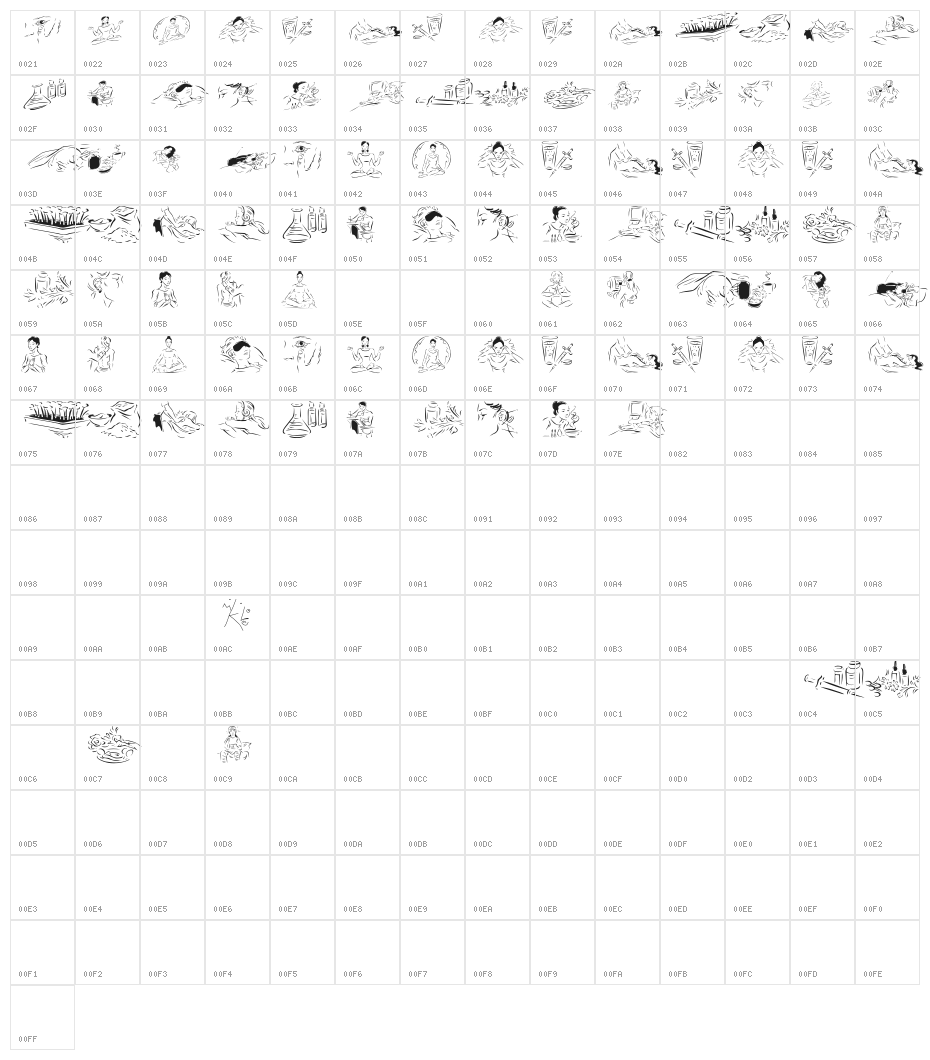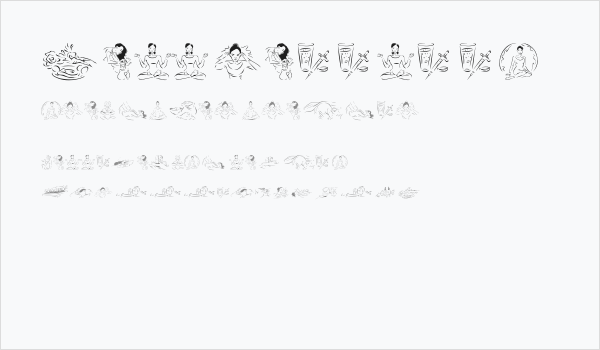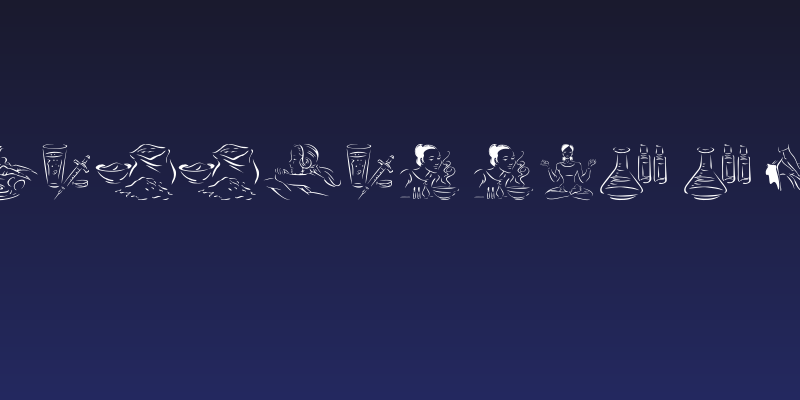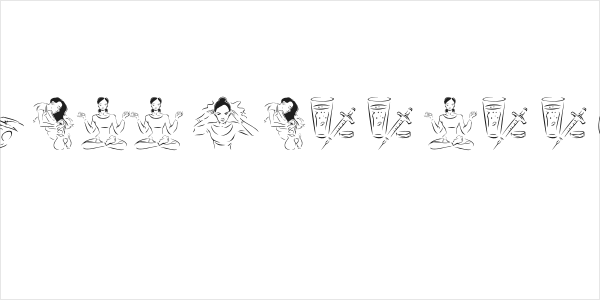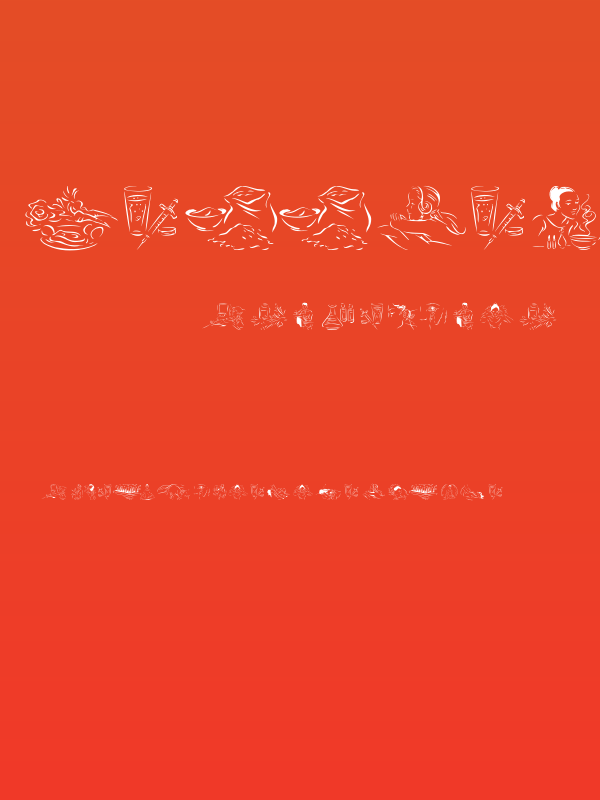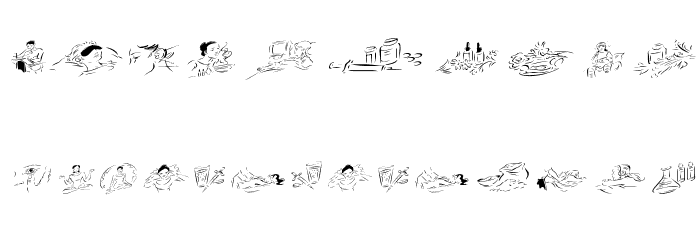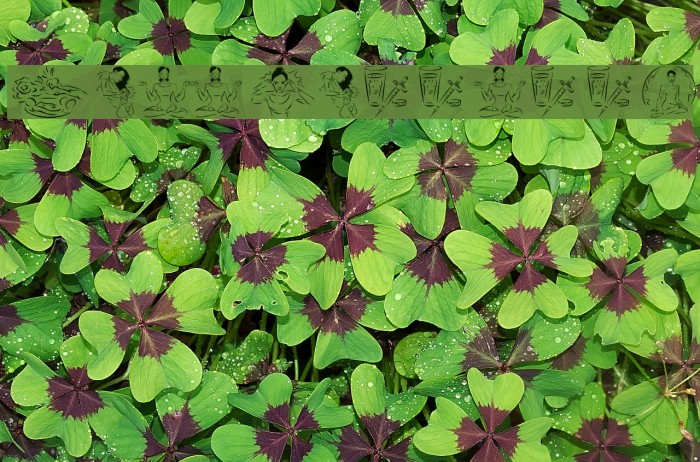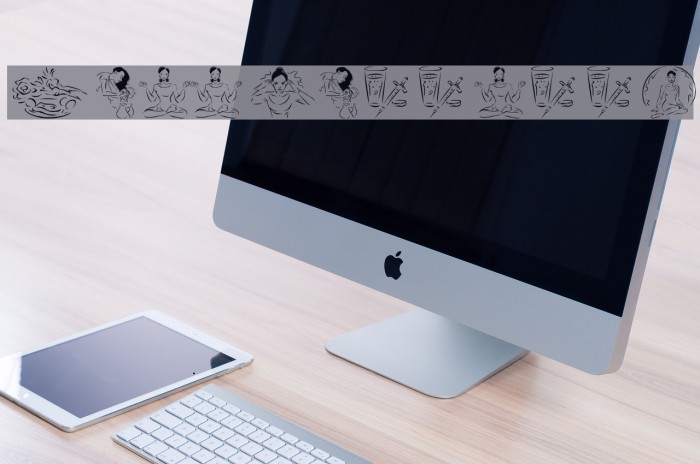
WellnessBoom Font
| Stile generale | Decorative, Hand-drawn, Relaxed |
| Caso d'uso | Logos, Headlines, Themed graphics, Visual accents |
| Progetti proposti | Wellness branding, spa menus, event invitations, posters, holistic health websites. |